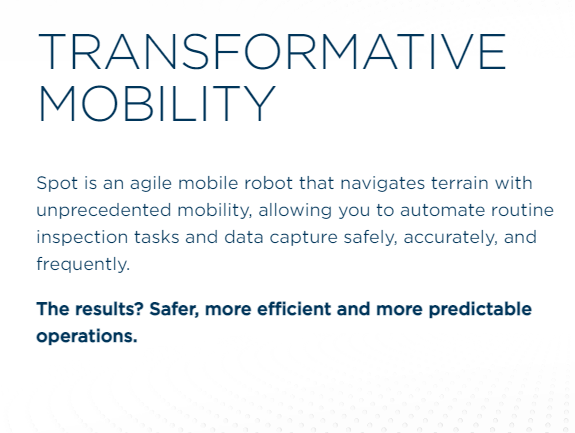
Sitem için FONT önerisi
Sitemde kullandığım
''Gotham''
fontunu değiştirmek istiyorum. Uzay ve havacılık ile ilgili olacak olan bu sitede font önerilerinizi bekliyorum.
Site içinde font görüntüsü;
Buna benzeyen diyorsanız: Raleway ya da Montserrat, onun haricinde diyorsanız bugünlerde favorim olan Inter.
Son zamanlarda favorim Poppins